20 e oltre Font liquidi per progetti tipografici espressivi
La raccolta propone oltre venti font liquidi pensati per trasformare titoli e lettering in elementi visivi dinamici, morbidi e ricchi di movimento. Queste tipografie sono particolarmente efficaci quando il testo deve diventare il fulcro grafico di un progetto, non soltanto un supporto informativo.
Stili fluidi tra acqua, gocce e superfici elastiche
I caratteri selezionati reinterpretano l’effetto liquido in modi molto diversi: colature d’inchiostro, onde, bolle, schizzi d’acqua, riflessi e lettere deformate. Dripdrop, ad esempio, sviluppa un’estetica più grintosa e vicina ai graphic design Y2K, mentre Liquify e Blue Soak puntano su forme che evocano acqua in movimento e gocce irregolari.
La varietà di approcci permette di adattare il linguaggio liquido sia a progetti energici sia a composizioni più organiche e raffinate.
Font per branding, poster e packaging
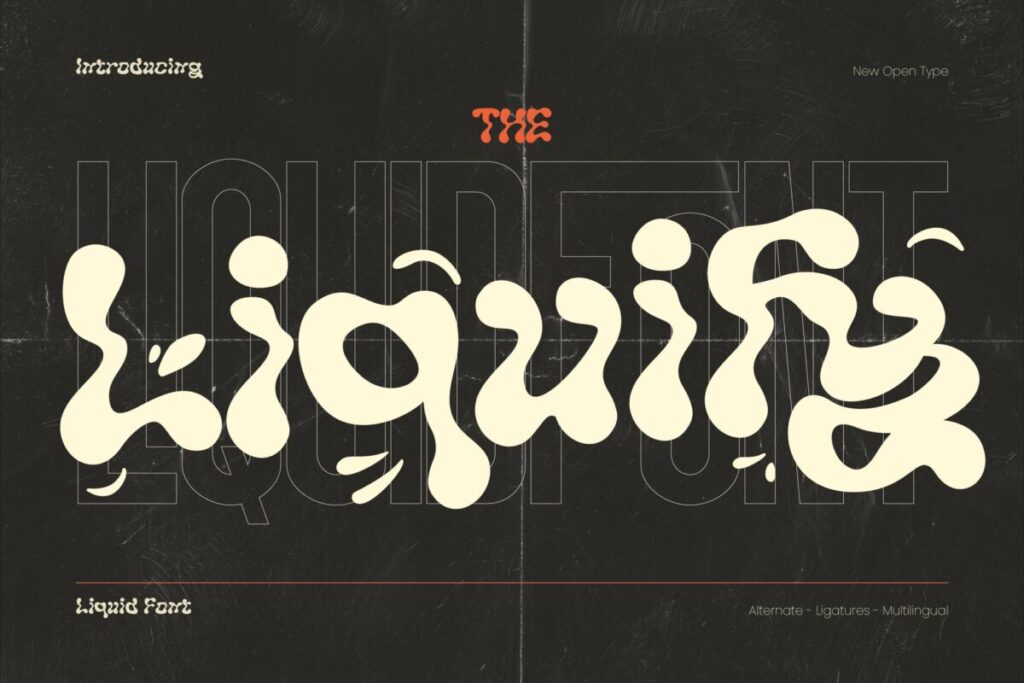
Questa risorsa risulta utile a chi deve progettare identità visive non convenzionali, locandine, copertine musicali, inviti, campagne digitali o confezioni di prodotto. Caratteri come Dynamic Drips, Wet Slab, Eborame e Unflow sono indicati per titoli grandi, poiché sfruttano forme marcate e decorative che mantengono una presenza scenica anche in composizioni essenziali.
L’uso ideale è nei testi brevi, dove la riconoscibilità e l’impatto contano più della lettura prolungata.
Proposte giocose per progetti giovani e creativi
Alcuni font della selezione hanno un tono più leggero, rotondo e immediato, adatto a brand per bambini, eventi estivi, grafiche social e prodotti dal carattere informale. Happytale lavora su volumi morbidi e simili a bolle, Wakaba richiama il moto delle onde, mentre Hydration utilizza lettere ondulate per comunicare energia e freschezza.
Queste soluzioni aiutano a costruire una comunicazione visiva amichevole, vivace e facilmente memorabile.
Estetiche psichedeliche, horror e sperimentali
La raccolta non si limita ai richiami acquatici: include anche opzioni per design inquietanti, alternativi o futuristici. Grims Acid può valorizzare contenuti a tema Halloween e horror grazie alle sue colature, mentre Aderoy, Elastix e Nockwell esplorano deformazioni psichedeliche e forme più sperimentali.
Sono caratteri da usare con intenzione, soprattutto per poster, moda, musica e campagne che vogliono distinguersi con un’identità visiva audace.
Funzioni tecniche e flessibilità dei caratteri
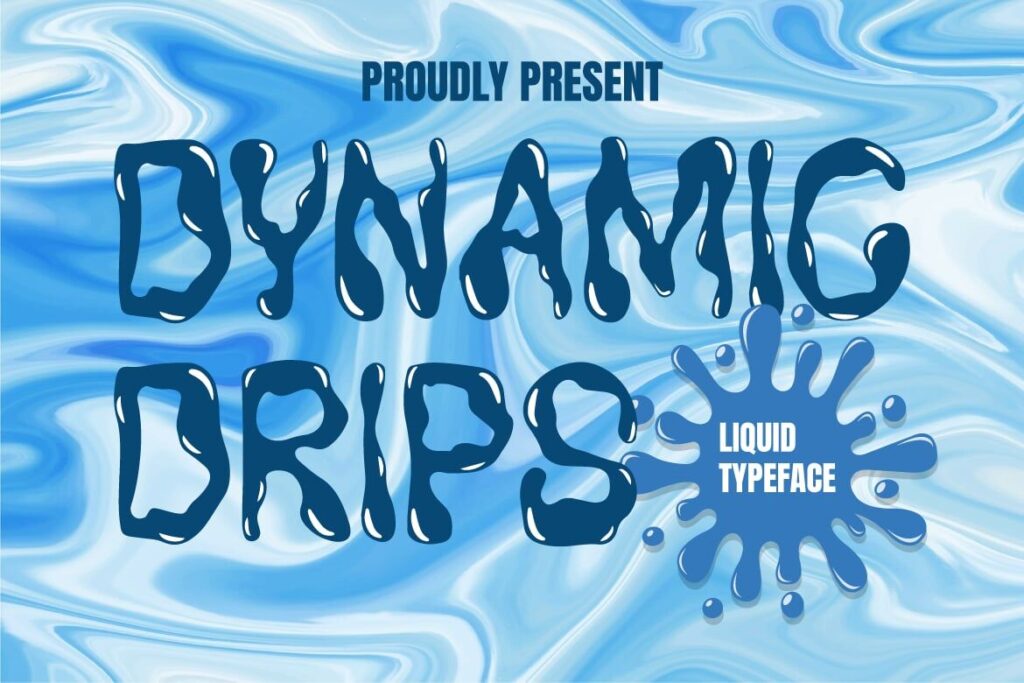
Diversi font includono maiuscole, minuscole, numeri, segni di punteggiatura, legature, varianti alternative e supporto multilingue. Bryzhi, per esempio, offre variazioni automatiche e alternative stilistiche OpenType, mentre altri caratteri vengono distribuiti nei formati OTF, TTF, WOFF e WOFF2.
Alternative gratuite per sperimentare
La pagina comprende anche alcune proposte gratuite per uso personale, tra cui Acidrop, Liquid Alien, Oleho Senthor e Plumpy Bold. Questi font consentono di testare l’effetto liquido in titoli, post social, progetti scolastici o bozze creative senza dover subito acquistare una licenza commerciale. Per l’uso in branding, pubblicità o prodotti destinati alla vendita occorre però verificare sempre i termini specifici della licenza.
Un punto di partenza per una tipografia in movimento
I font liquidi offrono un modo diretto per dare ritmo, matericità e personalità alle parole, specialmente in contesti dove il lettering deve comunicare emozione prima ancora del contenuto.
Proseguendo nella risorsa è possibile esplorare tutte le risorse e trovare il carattere più adatto al proprio progetto creativo.